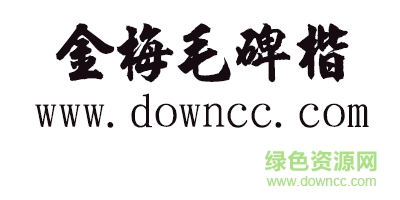
金梅毛碑楷字體是小編比較喜歡的一類字體,這款字體線條略粗,字體外觀規(guī)范整潔,可用于文字類排版!喜歡這款字體的用戶快來綠色資源網(wǎng)下載吧。
金梅毛碑楷字體是金梅字體庫中的一款中文簡體字體。字體端正,比楷體略粗,看起來很醒目,可用過廣告設(shè)計(jì)等行業(yè),趕快下載體驗(yàn)吧!